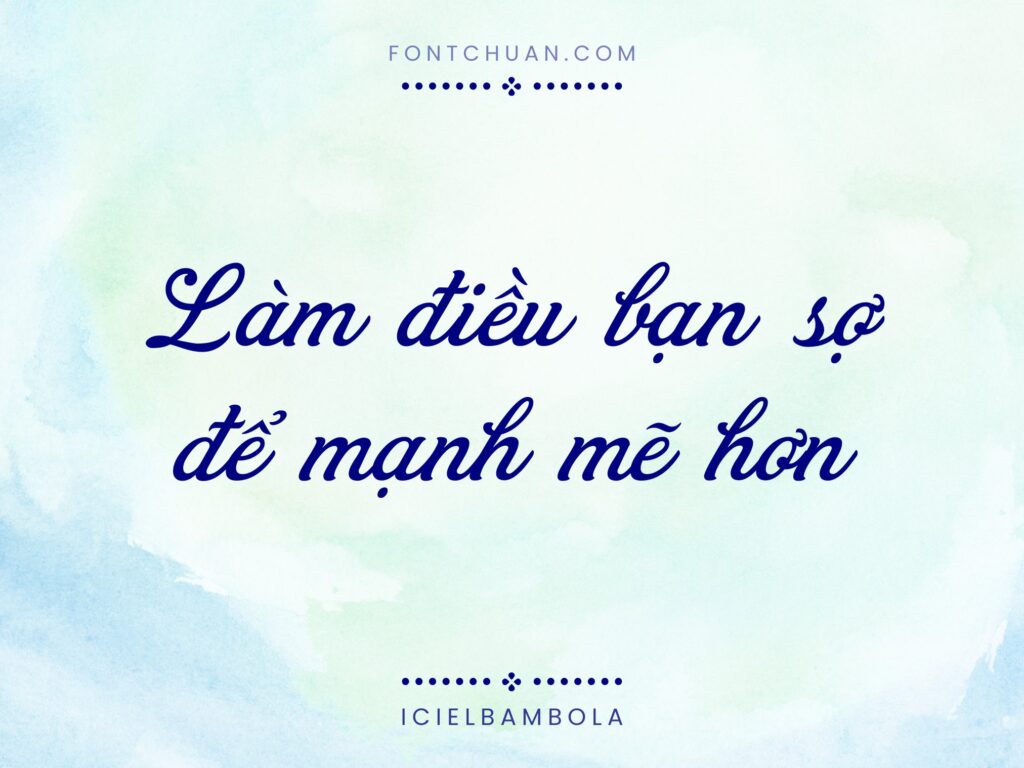
Font iCiel Bambola Việt Hóa
Bambola là một font chữ script thanh lịch, mang phong cách viết tay với những đường nét uốn lượn tinh tế và các nét trang trí phức tạp, tạo nên vẻ đẹp sang trọng và duyên dáng. Font này được thiết kế bởi Ricardo Rousselot, nổi tiếng với các tác phẩm chữ nghệ thuật tinh xảo. Để hỗ trợ cộng đồng thiết kế Việt Nam, Iciel đã Việt hóa font Bambola, giúp font này hỗ trợ đầy đủ tiếng Việt cùng hơn 200 ngôn ngữ khác. Phiên bản Bambola Việt hóa đã được thành viên Font Chuẩn sưu tầm và đăng tải, mang đến sự lựa chọn phong phú cho các nhà thiết kế.
Về đặc điểm thiết kế, Bambola sở hữu các ký tự nối liền mạch với những vòng xoáy và nét cong tinh tế, tạo nên sự liên kết tự nhiên giữa các chữ cái. Font này rất phù hợp cho các thiết kế như thiệp cưới, thương hiệu cao cấp, bao bì sản phẩm sang trọng và các tiêu đề trang trí. Ngoài ra, Bambola cũng là lựa chọn lý tưởng cho các ngành nghề như quảng cáo, thiệp cưới, ẩm thực và giáo dục, mang lại phong cách chuyên nghiệp và thu hút. Font này cũng thích hợp để sử dụng trong các sự kiện như Valentine, Sinh nhật và các dịp lễ hội.